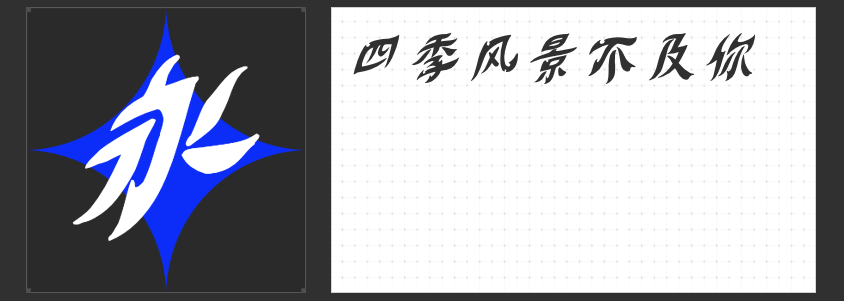
招牌设计字体精选:四款彰显品牌魅力的字体推荐
在店铺招牌设计中,字体不仅是信息传递的载体,更是品牌个性的视觉化表达。以下四款字库字体以其独特的风格与强大的视觉张力,成为招牌设计的优选方案,助力商家在方寸之间传递品牌精髓。
一、造字侠醉春风简繁 苍劲
这款字体以自由率真的笔触展现灵动之美,单字结构松弛而不失周正,圆润的笔画与自然的粗细过渡,赋予招牌活泼亲民的气质。其独特的字形风貌尤其适合餐饮、文创等需要传递轻松氛围的场景,如咖啡馆招牌或儿童品牌门店,能让顾客在第一眼接触中感受到品牌的温度与活力。
二、造字侠侠道简繁
以桀骜不驯的书法气质脱颖而出,字形饱满且布白均匀,飞白与夸张处理强化了视觉冲击力。转折处的突出笔画与回锋收笔设计,在保持辨识度的同时,传递出品牌独树一帜的态度。适用于酒吧、潮牌店或艺术空间,其鲜明的节奏感能瞬间抓住行人视线,成为街头吸睛利器。
三、万人字造一骏炎黄图腾体 大粗
右上倾斜的个性书法设计打破常规,粗犷的笔画与强烈的视觉张力,让招牌在密集的商业环境中脱颖而出。这款字体既保留传统书法的韵味,又以现代手法重构字形结构,特别适合茶楼、书店或文化展馆,既能彰显文化底蕴,又能通过倾斜动态营造进取之势。
四、励字魔方黑简
作为简约风格的代表,这款字体以方正无装饰的造型实现高效信息传递。横竖笔画的粗细对比与方头方尾的设计,在保持易读性的同时,通过几何美感传递现代专业感。适用于科技产品店、极简风格买手店或商务服务机构,其醒目的视觉表现能强化品牌的专业形象。
四款字体各具特色,从传统文化演绎到现代简约表达,覆盖了招牌设计的多元需求。设计师可根据品牌调性与空间环境灵活选用,让字体成为传递品牌故事的首张名片。